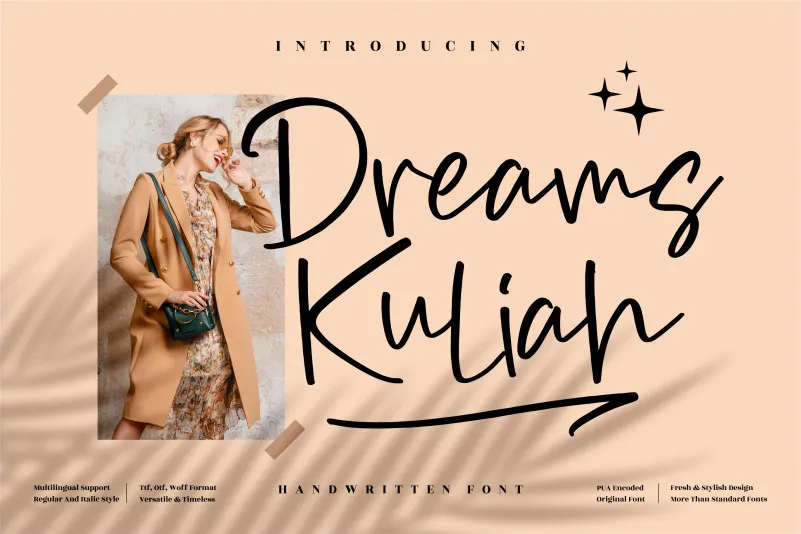
Dreams Kuliah Font
A fonte Dreams Kuliah é perfeita para projetos onde você deseja uma pitada de handwritten natural e elegante. Ideal tanto para identidades visuais detalhadas quanto para aplicações práticas como etiquetas, materiais de embalagem ou material promocional. Suas linhas delicadas e estilo casual combinam perfeitamente com a sua necessidade de criar um design autêntico e único. Seja em camisas personalizadas, capas de livros, cartões de visita, mensagens de felicitações ou até mesmo em uma foto de viagem, esta fonte irá garantir que seu projeto fique com aquele toque especial que torna a diferença entre um produto de luxo e um objeto de valor. Ideal para todas as suas criações que precisam de um toque autêntico e pessoal, a Dreams Kuliah é uma excelente escolha para qualquer designer gráfico.